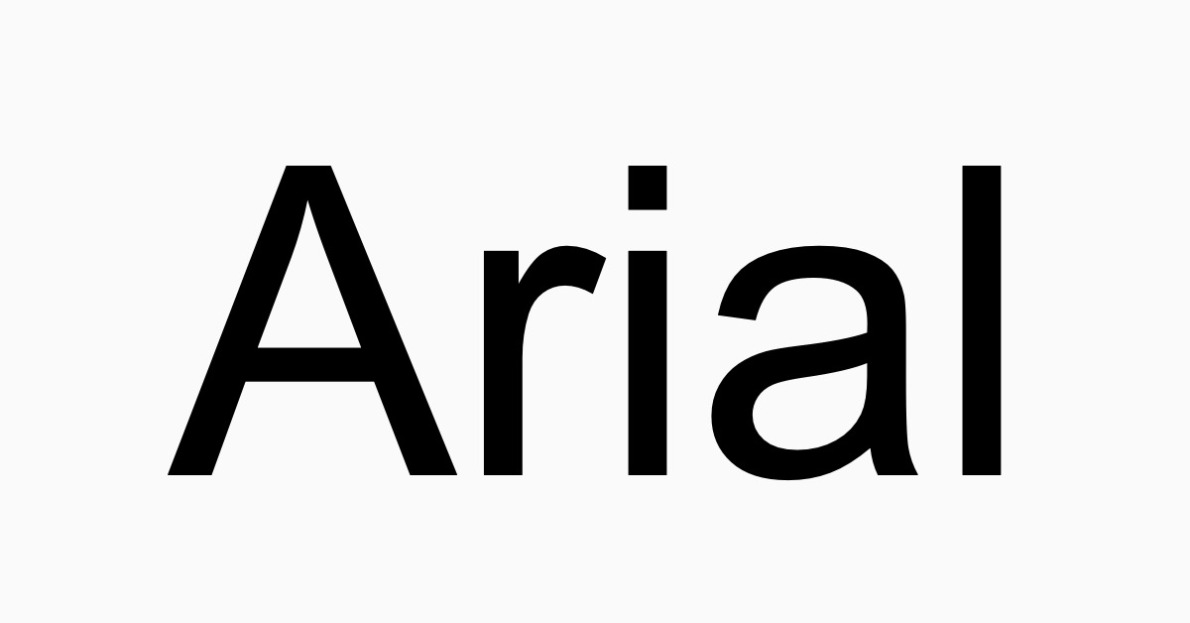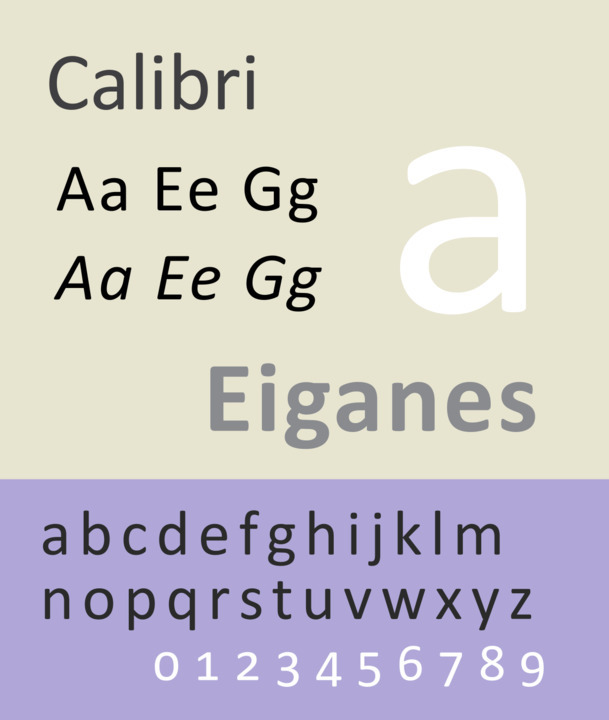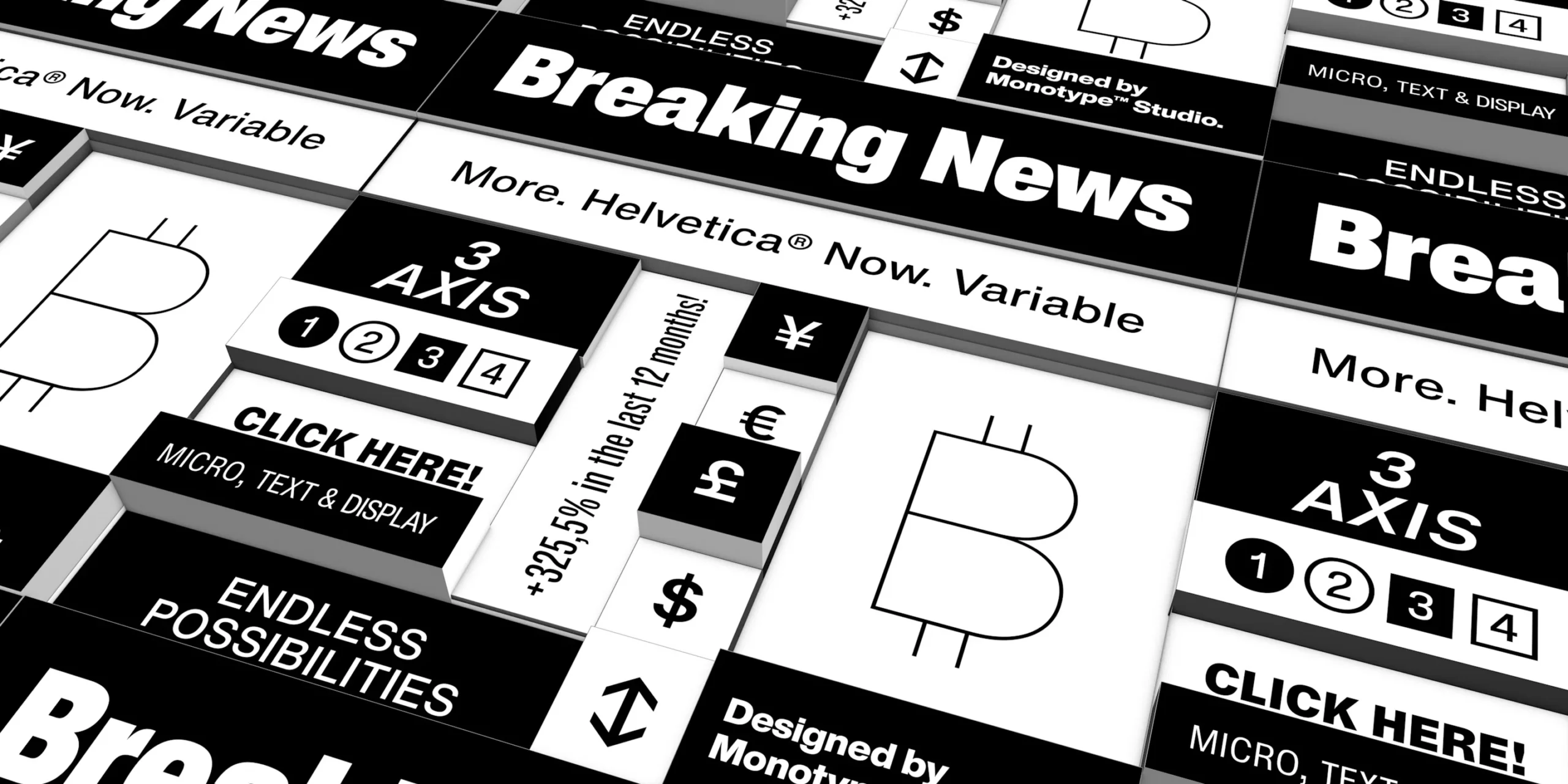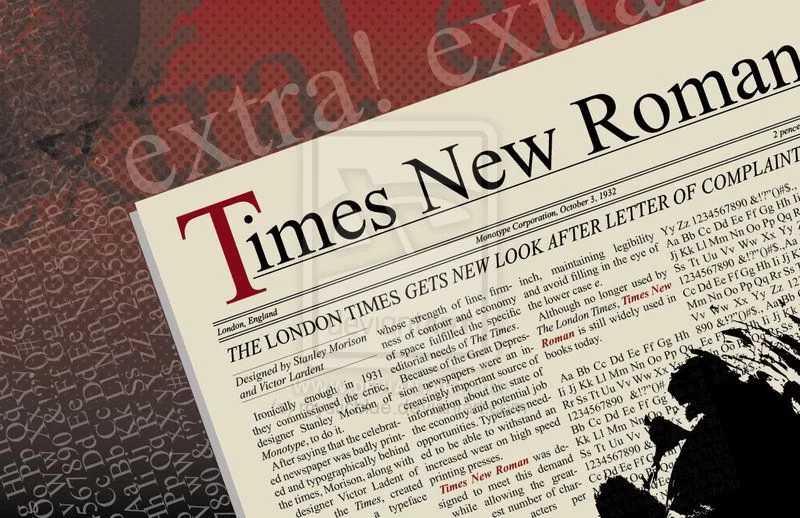
4 font chữ nổi tiếng mà bạn có thể đã biết
4 font chữ nổi tiếng mà bạn có thể đã biết. Với hàng triệu font chữ hiện nay thì có một vài font chữ cực kỳ nổi tiếng và chắc chắn bạn đã biết 1 trong số chúng.
1. Times New Roman
Times New Roman được sử dụng lần đầu tiên trên tờ The Times của Anh vào năm 1931. Font chữ thông dụng này ra đời vì nhà xuất bản cho rằng họ cần một font “cứng cáp” hơn so với các font chữ đang được sử dụng ở thế kỷ 19.
Cha đẻ của font Times New Roman là nhà thiết kế kiểu chữ nổi tiếng Stanley Morison, cùng với sự giúp đỡ của nhà soạn thảo Victor Lardent đã bắt đầu lên ý tưởng về font chữ mới với hai mục tiêu: tối đa hóa số lượng chữ trên trang và giúp đọc giả đọc nhanh hơn.
Việc tối đa hoá số lượng chữ trên một trang sẽ giúp việc in ấn tiết kiệm hơn – một điều kiện cần thiết trong kinh doanh báo chí.
Lúc bấy giờ, Times New Roman rất được ưa chuộng và sử dụng rộng rãi trên nhiều tờ báo, sau đó nhanh chóng trở thành font chữ phổ biến trong các nhà máy in.
Trải qua nhiều thập kỷ, Times New Roman đã trở thành một trong những font chữ mặc định luôn có sẵn trong các thiết bị điện tử, càng chứng minh rằng người dùng cực yêu thích font chữ này.
2. Calibri
Calibri được xem là “em út” trong danh sách này vì nó chỉ mới ra đời vào năm 2004. Câu chuyện tạo ra Calibri bắt đầu khi nhà thiết kế font chữ Lucas de Groot được tuyển vào làm việc cho một khách hàng “bí mật”. Vị khách hàng này đã yêu cầu một font chữ mang nét hiện đại và phải tối ưu hoá cho việc hiển thị trên màn hình máy tính.
De Groot đã tạo ra Calibri bằng cách chỉnh sửa lại bộ font chữ mà ông đã thiết kế từ bảy năm trước, chỉ thay đổi về độ rộng và độ cong của chữ cái. Sau khi hoàn thành font chữ, ông mới biết “vị khách hàng bí mật” kia chính là Microsoft.
Dù “sinh sau đẻ muộn” nhưng Calibri luôn được mọi người ưu ái sử dụng. Bằng chứng là font chữ này được đặt làm font chữ mặc định cho tất cả các phần mềm của Microsoft từ năm 2007.
3. Helvetica
Helvetica là một trong những font chữ có ảnh hưởng nhất của thế kỷ 20. Helvetica được phát triển vào năm 1957 bởi 2 nhà thiết kế kiểu chữ người Thụy Sĩ là Max Miedinger và Eduard Hoffmann, và sau này được công ty in ấn Linotype mua lại.
Đây là font chữ mặc định được các nhà thiết kế đồ họa ưa thích, được sử dụng rộng rãi trong ngành nghệ thuật và thời trang.
Có không ít công ty lớn trên thế giới sử dụng font Helvetica cho logo của mình, điển hình như: Target, Jeep, JCPenney…Điều này càng chứng tỏ sức ảnh hưởng của Helvetica trong văn hoá đại chúng.
Apple từng có một thời “say đắm” Helvetica khi áp dụng font chữ này vào tất cả sản phẩm của họ từ 2007 đến tận 2015. Phải đến tận năm 2015, khi Apple Watch ra mắt, Apple mới nhận ra rằng Helvetica không còn phù hợp với hệ sinh thái của mình.
Lý do vì khả năng hiển thị chữ trên màn hình cỡ nhỏ của Helvetica không tối ưu. Apple đã thay thế Helvetica bằng font San Francisco – font chữ thích hợp với các thiết bị có size màn hình nhỏ như Apple Watch hay Iphone.
4. Arial
Arial được thiết kế bởi Robin Nicholas và Patricia Saunders vào năm 1982. Font chữ này được tạo ra với mục đích phục vụ cho ngành kỹ thuật số. Do đó, nó mang font cách ‘đương đại’ hơn so với các font chữ tiền nhiệm. Lần đầu tiên Arial được sử dụng là vào năm 1992 trên hệ điều hành Windows 3.1.
Arial đã phải đối mặt với nhiều ý kiến tiêu cực vì quá giống với font chữ tiền nhiệm “Helvetica”. Nhiều người còn cho rằng Microsoft cố tình tạo ra một kiểu chữ “nhái” Helvetica để tránh phải trả phí bản quyền cho Linotype. Theo phân tích, mặc dù Arial được tạo ra dựa trên họ kiểu chữ Monotype Grotesque, nhưng lại gần giống với Helvetica ở độ rộng (glyph widths) và tỷ lệ.
Dù bị ném đá như thế nhưng Arial vẫn là lựa chọn phổ biến cho các ấn phẩm quảng cáo, áp phích, thiết kế sách bởi tính dễ đọc khi hiển thị ở mọi kích thước lớn nhỏ.